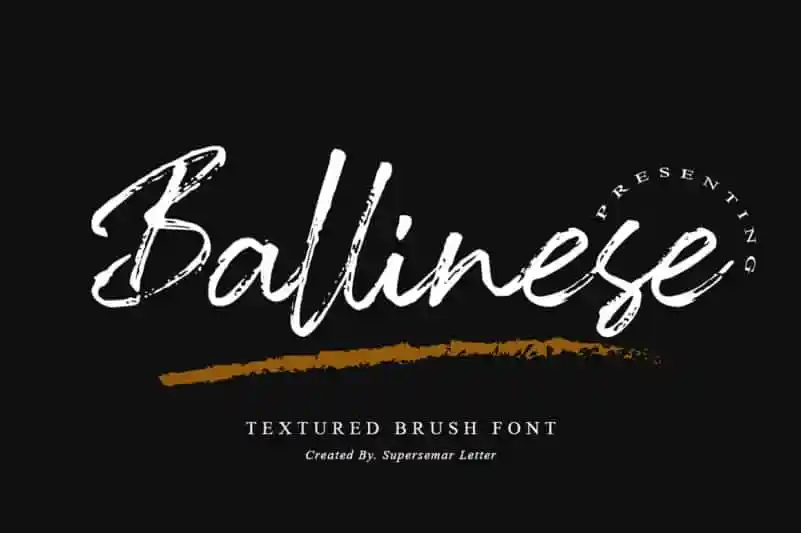
Ballinese Brush Font – Fonte Grátis
Ballinese Brush Font
A Ballinese Brush Font é uma deliciosa mistura de elegância e naturalidade que vai revolucionar a forma como você apresenta sua tipografia no Brasil. Seu charme genuíno e seu tom relaxado, mais próximo do estilo à mão, irá rejuvenescer seus textos para um visual ainda mais autêntico e único. Foi criada pelo font designer Supersemar Letter. O que torna esta fonte ainda mais inovadora é a inclusão de ligaturas especiais que aparecem quando você pressiona simultaneamente os caracteres “+” (mais) e “=” (igual). Isso não apenas dá um toque único às letras, mas também as transforma em designs incríveis. Ideal para headlines, logos, panfletos, embalagens, camisetas e muito mais. Seja você criando a capa de seu próximo álbum musical, estilizando o logotipo da sua empresa ou apenas criando um design de t-shirt personalizado, Ballinese Brush Font tem tudo o que você precisa para transformar seus trabalhos em verdadeiras obras de arte. O estilo à mão desta fonte é perfeito tanto para um ambiente mais formal quanto para um visual descontraído e vibrante — seja qual for seu projeto, este será uma excelente escolha.